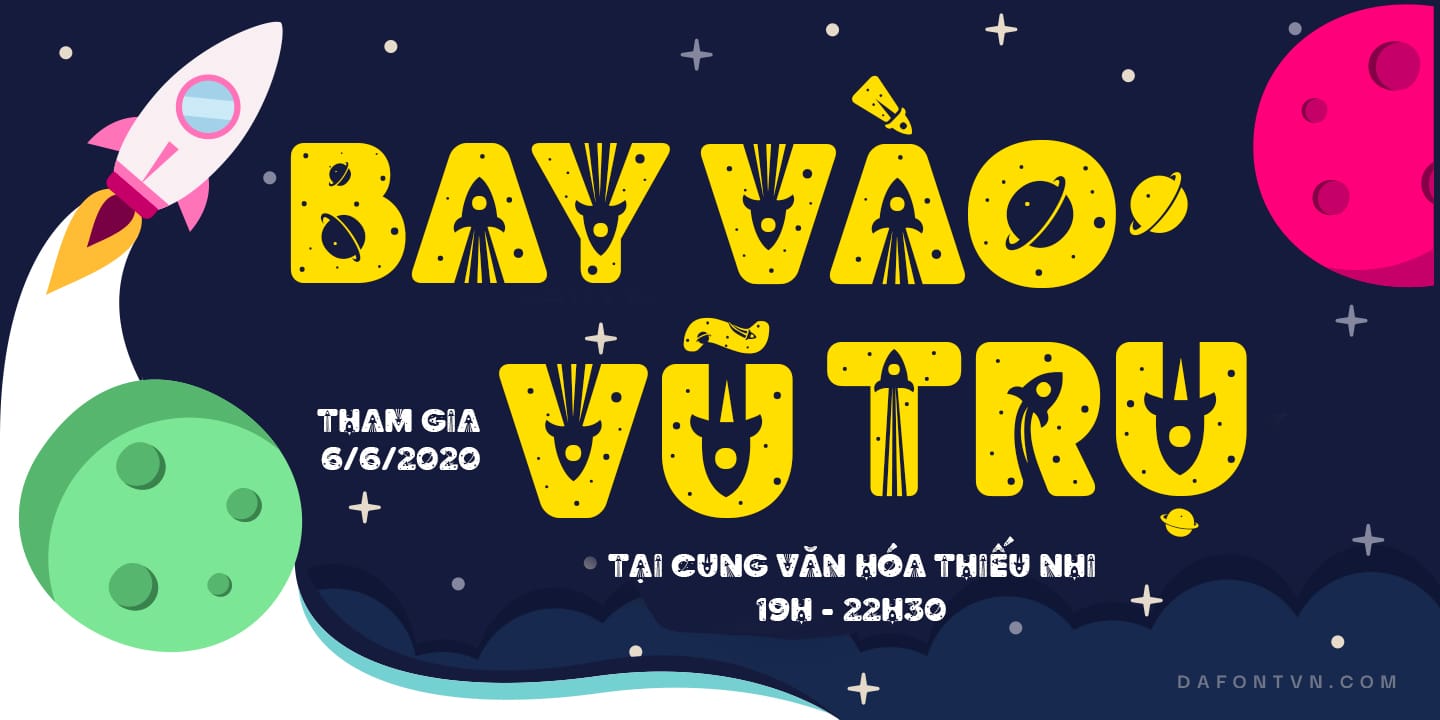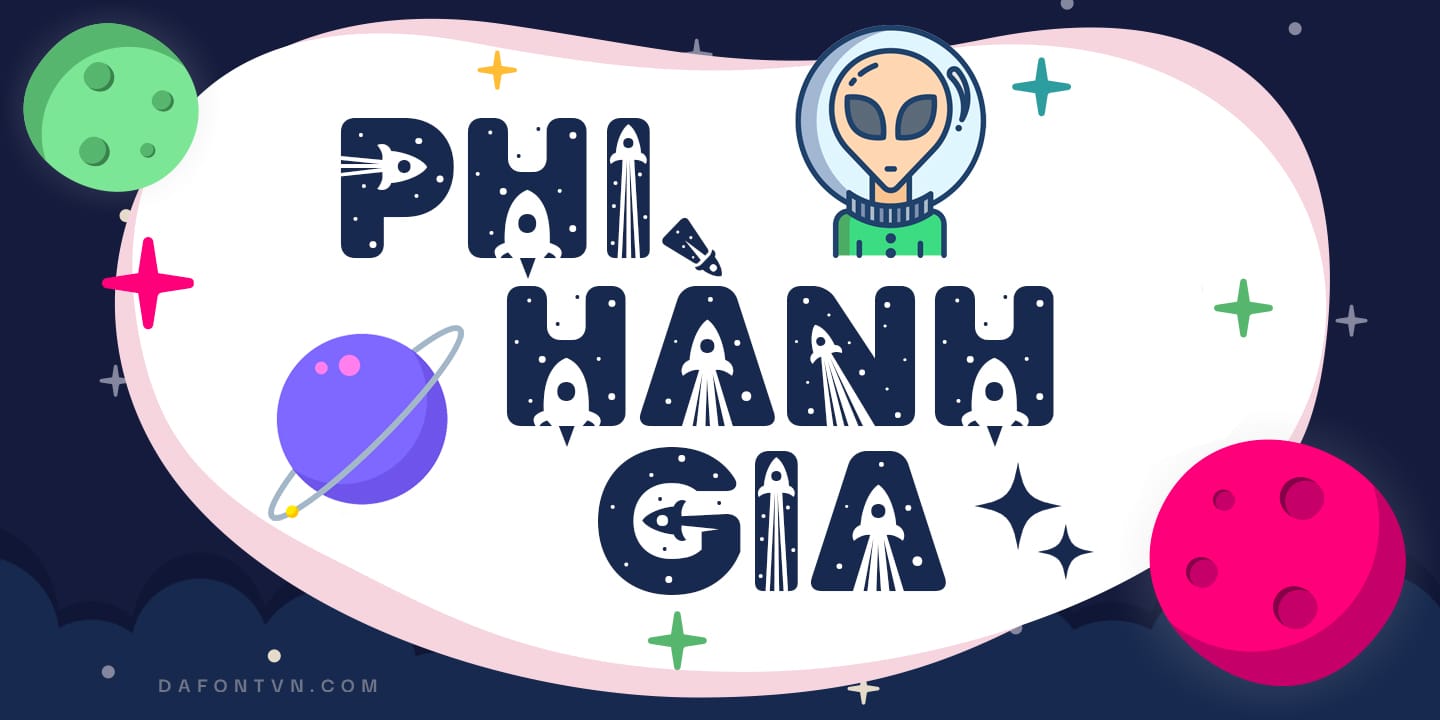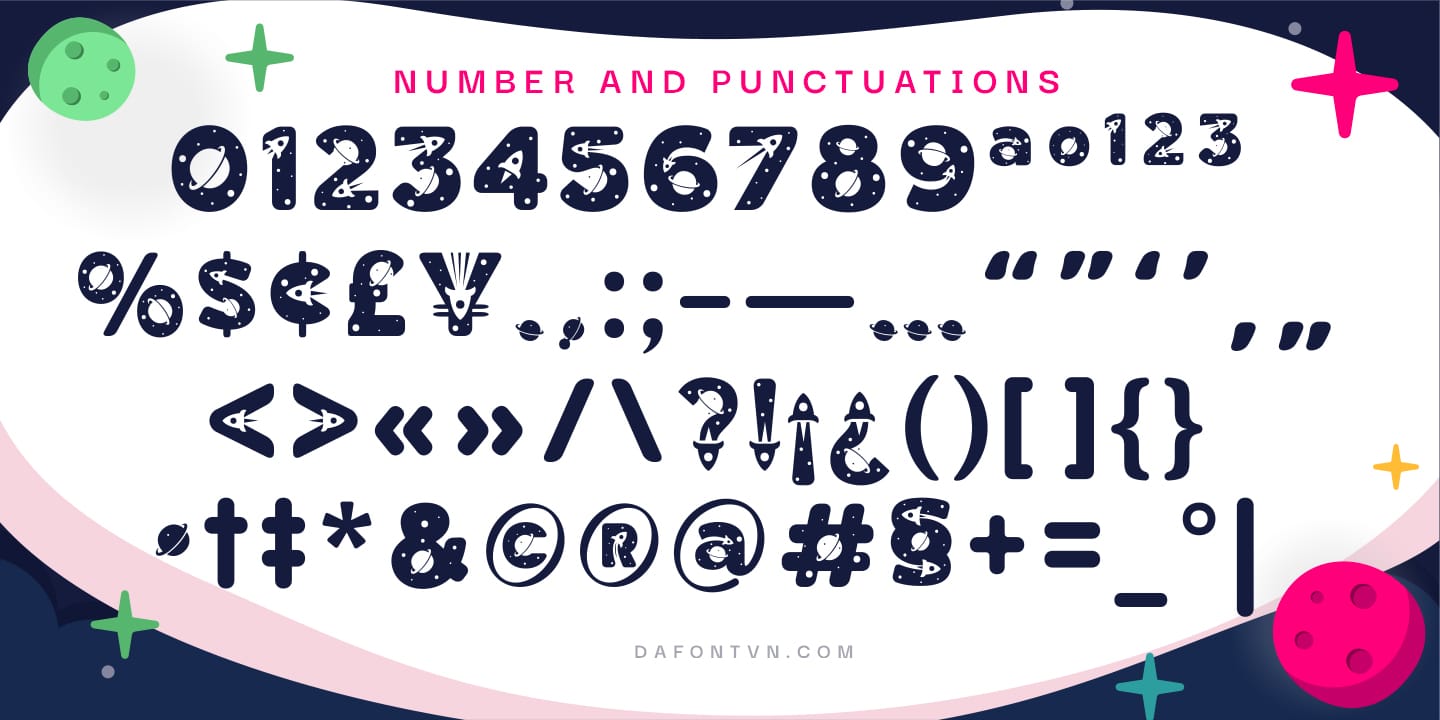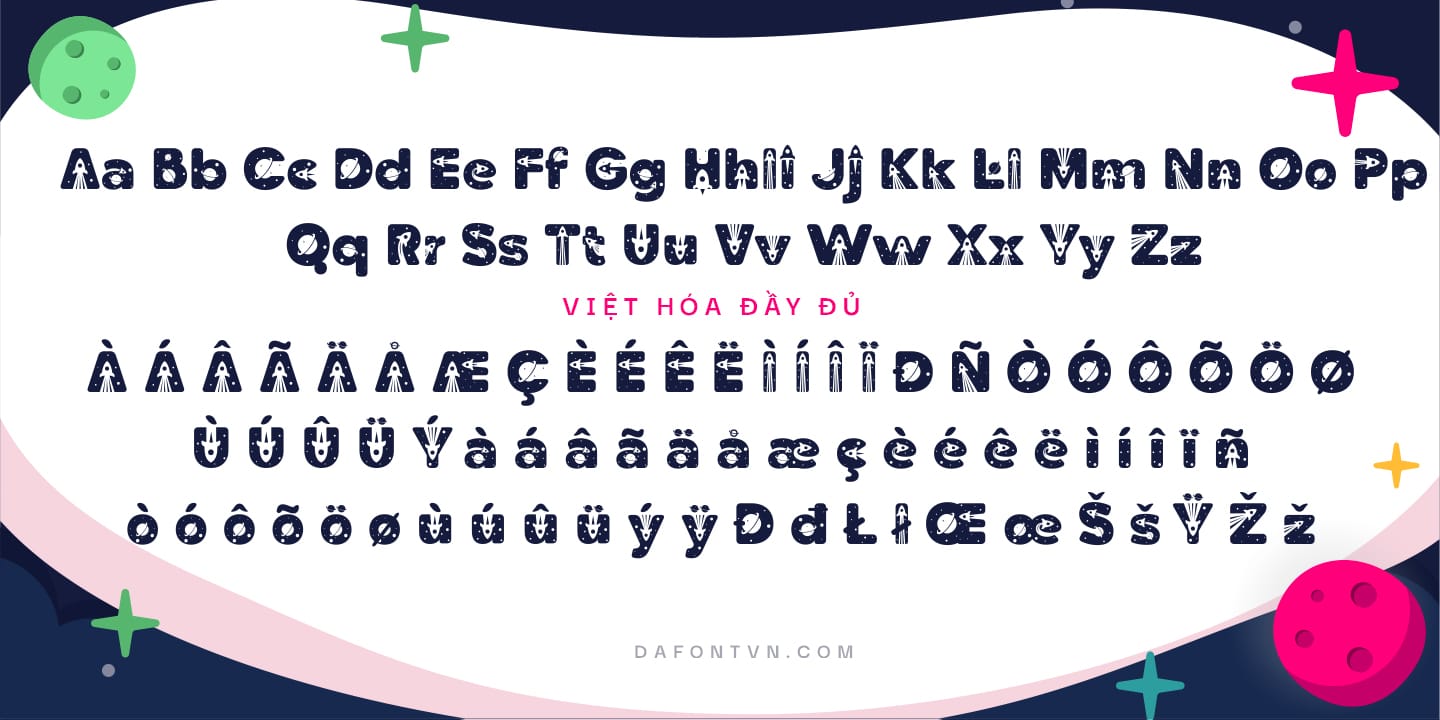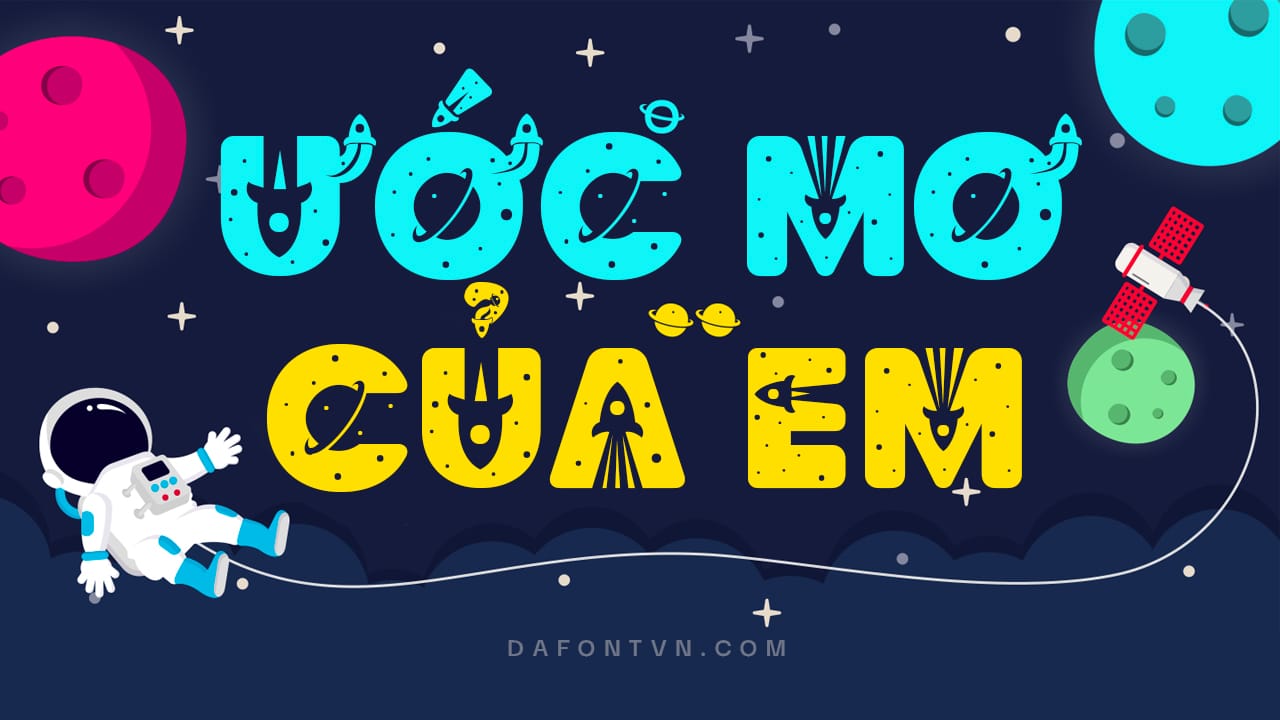
Space Quest Font là 1 kiểu phông chữ hiển thị vô cùng độc đáo và thú vị lấy cảm hứng từ vũ trụ bao la với các kỳ thú mà con người chưa thể khám phá hết. Các nét chữ được thiết kế cực đẹp, các chữ cái đậm và chunky của nó làm cho phông chữ này phù hợp với nhiều loại thiết kế. Space Quest sẽ biến bất kỳ ý tưởng sáng tạo nào thành một điểm nổi bật thực sự!Font phù hợp cho các thiết kế kiểu sự kiện, bìa sách liên quan đến vũ trụ, không gian. Font Việt hóa bởi NVN, các dấu đã được vẽ lại cho phù hợp với các nét chữ. Ngoài ra đã được kerning, mã hóa PUA để sử dụng dễ dàng trên bất kỳ thiết kế nào.